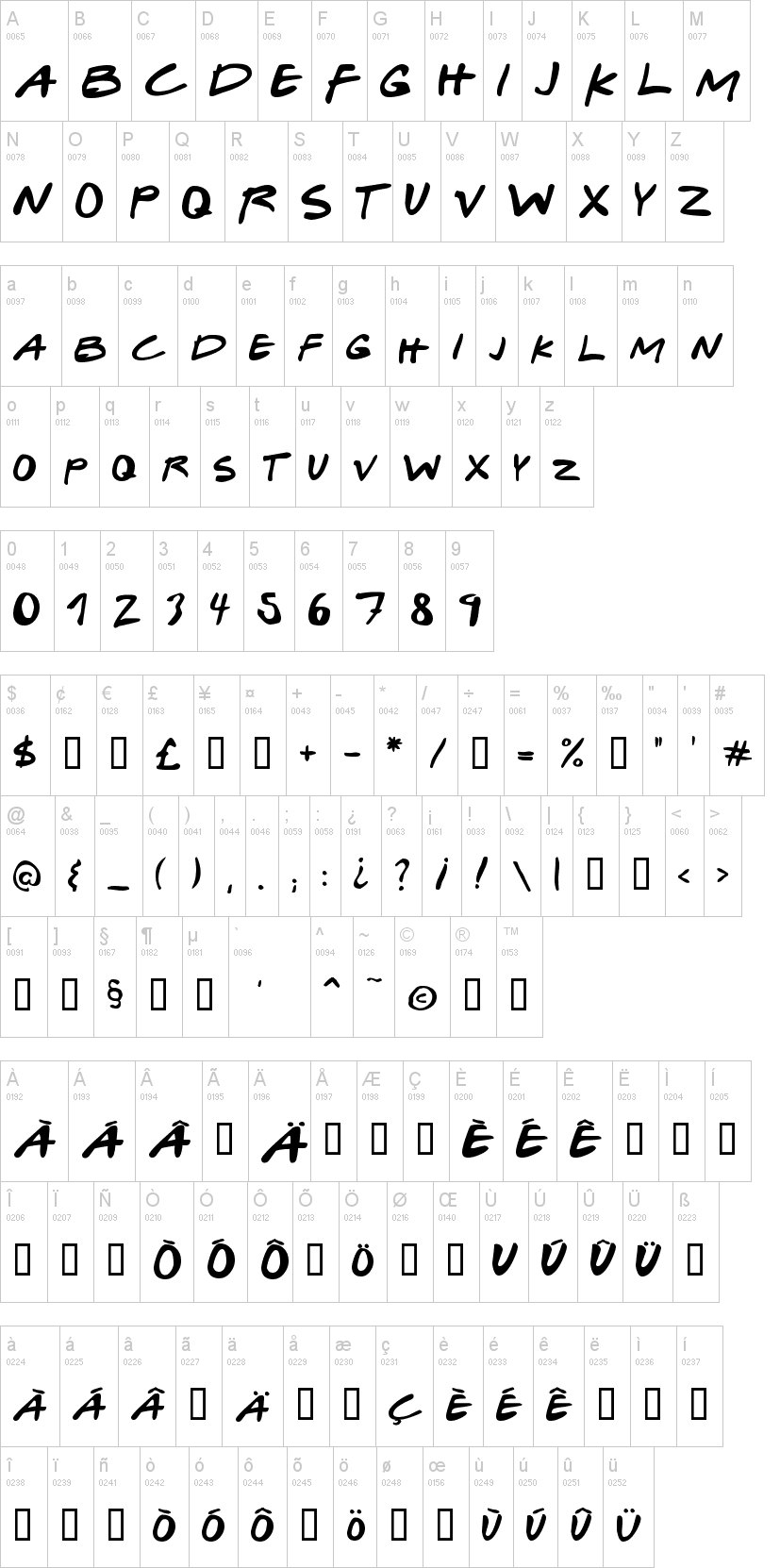
Gabriel Weiss' Friends
Gabriel Weiss' Friends 是由美国设计师 Gabriel Weiss 创作的一款手写体字体,它具有优雅、活泼、灵活的特点,适用于各种场合、应用场景,如拼图、海报、标志、标题等等。它有着轻松、活泼、可爱的气息,可以让你的设计更有趣、更加有趣。它的字体细节清晰,可以让你的文字更加具有个性,同时也可以让你的设计更加精致。
Gabriel Weiss' Friends是一款非常不错的手写艺术字体,具有很好的视觉感,适合于文化类的宣传设计、商业类品牌的广告和产品包装设计以及个性化文字排版等较多场景。
Gabriel Weiss' Friends字符映射图